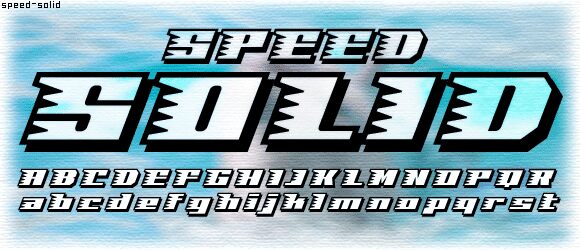
Speed Solid، من تصميم Masato Shimojima، هو خط مجاني بتصميم تقني (Techno) وعصري، يبدو وكأنه رسومات حركية جُمدت في منتصف السباق. تتميز الحروف بشكلها الضخم والمندفع للأمام، مع قصات حادة وحواف غير متماثلة تضفي على الخط طابع السرعة والضجيج وأجواء ألعاب الأركيد.
يتناسب الخط بشكل طبيعي مع شعارات الألعاب، وملصقات سباقات السيارات، وبانرات البث المباشر، والعناوين التي تتطلب إيصال الحركة قبل أن تقرأ الكلمة الثانية. وبفضل حروفه التي تجمع بين العرض والتماسك، فإنه مثالي أيضًا للشعارات المختصرة والرموز الحادة التي تحتاج إلى لمسة ميكانيكية مشحونة بالسرعة.